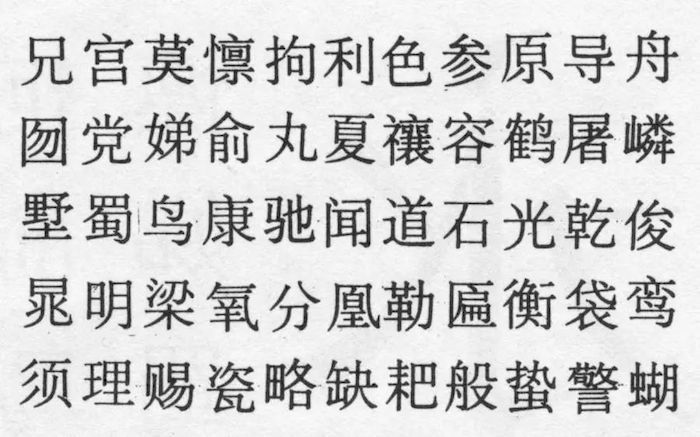
为《辞海》设计字体的他影响了一代代设计人 | 余秉楠
北京 | 中国首位AGI成员、清华大学教授余秉楠
87岁辞世,影响过一代又一代设计人
1992年,余秉楠是首位进入国际平面设计联盟(AGI)的华人设计师。他在书籍设计与字体设计都有非凡的成就,将网格系统与西文设计带到了中国。
余秉楠1933年出生于上海,1956年毕业于鲁迅美术学院,然后经过中国文化部的考核,余秉楠被选派到民主德国学习。余秉楠是新中国第一代选派的留学生。学成归国之后,创作了许多优秀的作品,出版了多本设计书籍,也成为清华大学、中央美术学院等多所高校的客座教授,影响了一代又一代的设计人。
“友谊体”是余秉楠的成名之作,也是对中国十分有历史意义的一套字体。留学期间,余秉楠接到老师给的第一个创作任务——一副适合用于多种排版、在中国使用的字体。
友谊体友谊体
作为中国人设计的第一套正文拉丁字母,友谊体在历年内获得了谷滕堡终生成就奖(首位亚洲获奖者)、“当代最佳印刷字体”奖、德国文化部长奖、东京艺术指导俱乐部(TDC)奖等多个奖项。
《辞海》的字体,宋一体、黑一体、宋二体、黑二体《辞海》的字体,宋一体、黑一体、宋二体、黑二体
1962年,余秉楠以优异的成绩从莱比锡毕业,谢绝了导师的挽留后便回国了。回国之后,余秉楠加入了上海印刷技术研究所,参与了为《辞海》设计的“宋一”、“黑一”和为《毛选》设计的“宋二”、“黑二”。1963年,余秉楠为《辞海》专门设计了一款拉丁文字体,名为“辞海细体”,该字体是新中国生产的第一套拉丁字母印刷活字。1987年,为了甩掉以往宋体的“角”,摆脱机械感,余秉楠通过马克笔的反复书写试验,最终创作完成了一款名为“圆宋”的印刷字体。(文/畹町)